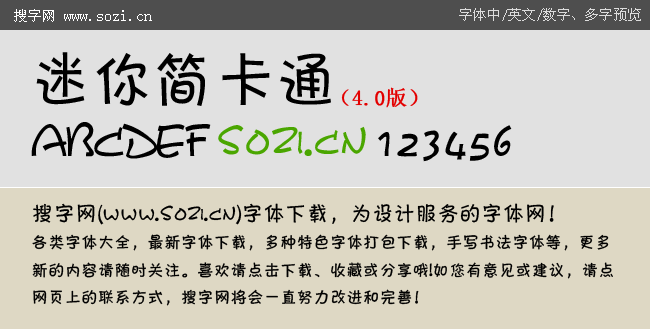
迷你簡(jiǎn)卡通體
搜字網(wǎng)提供一款迷你簡(jiǎn)卡通體下載。迷你簡(jiǎn)卡通體在字形設(shè)計(jì)上采用了“黑體”的基本筆形,參以行書(shū)的筆意、形態(tài),婉轉(zhuǎn)有度,斜正相倚,于傳統(tǒng)美中見(jiàn)時(shí)代氣息。適合兒童產(chǎn)品包裝、兒童書(shū)籍、卡通畫(huà)冊(cè)等廣告宣傳場(chǎng)合使用。